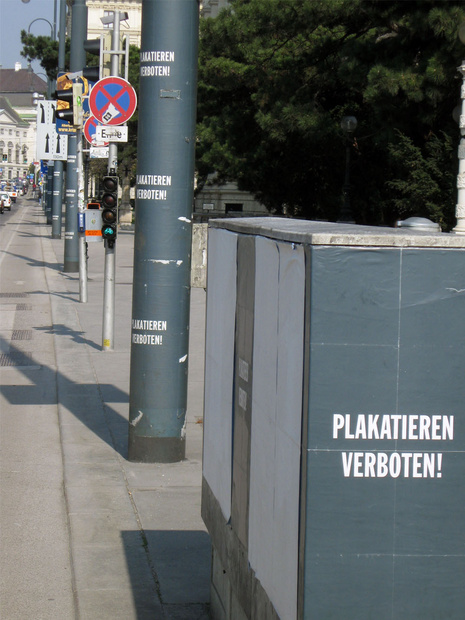
kampagne: „PLAKATIEREN VERBOTEN!“
in wien hängen seit längerem die widersprüchliche kampagne „PLAKATIEREN VERBOTEN“, des österreichischen werbeplakatmonopolisten GEWISTA.
nun würde ich gerne über die verwendete schrifttype bescheid wissen.
ich habe zuerst auf die trade gothic getippt, dies erwies sich allerdings aufgrund der runden, weniger konstruierten formen (beispielsweise im o) als trugschluss. was könnte es also noch sein?
hm, din eng glaub ich weniger – zu technisch.
aus demselben grund ist auch die trade gothic ausgeschieden.
gotham condensed sieht gut aus, allerdings finde ich noch keinen passenden schnitt. bewegt sich irgendwo zwischen bold und fett. dafür ist die punze des O wieder zu eng, hm...
gibt es noch weitere vorschläge oder ideen dazu?
sehr nah dran.
aber die anmutung des E stimmt nicht mit dem des Interstate E überein. auch das Ausrufezeichen ist bei der Interstate erst im unteren drittel nach unten hin verjüngend (siehe beihang), während der zusammenlauf bei der gesuchten schon oben beginnt.
sehr nah dran. aber die anmutung des E stimmt nicht mit dem des Interstate E überein. auch das Ausrufezeichen ist bei der Interstate erst im unteren drittel nach unten hin verjüngend (siehe beihang), während der zusammenlauf bei der gesuchten schon oben beginnt.
Es gibt die Aktion in diversen Ausführungen, unter anderem auch so:
Da ist es wohl die Interstate.
ah, interessant! – wusste ich nicht!
Bei der Aktion wurden mindestens zwei Fonts verwendet: Franklin Gothic Extra Condensed (zum Bild von Catspell passend) und Interstate Bold Compressed (zu meinem Bild passend).